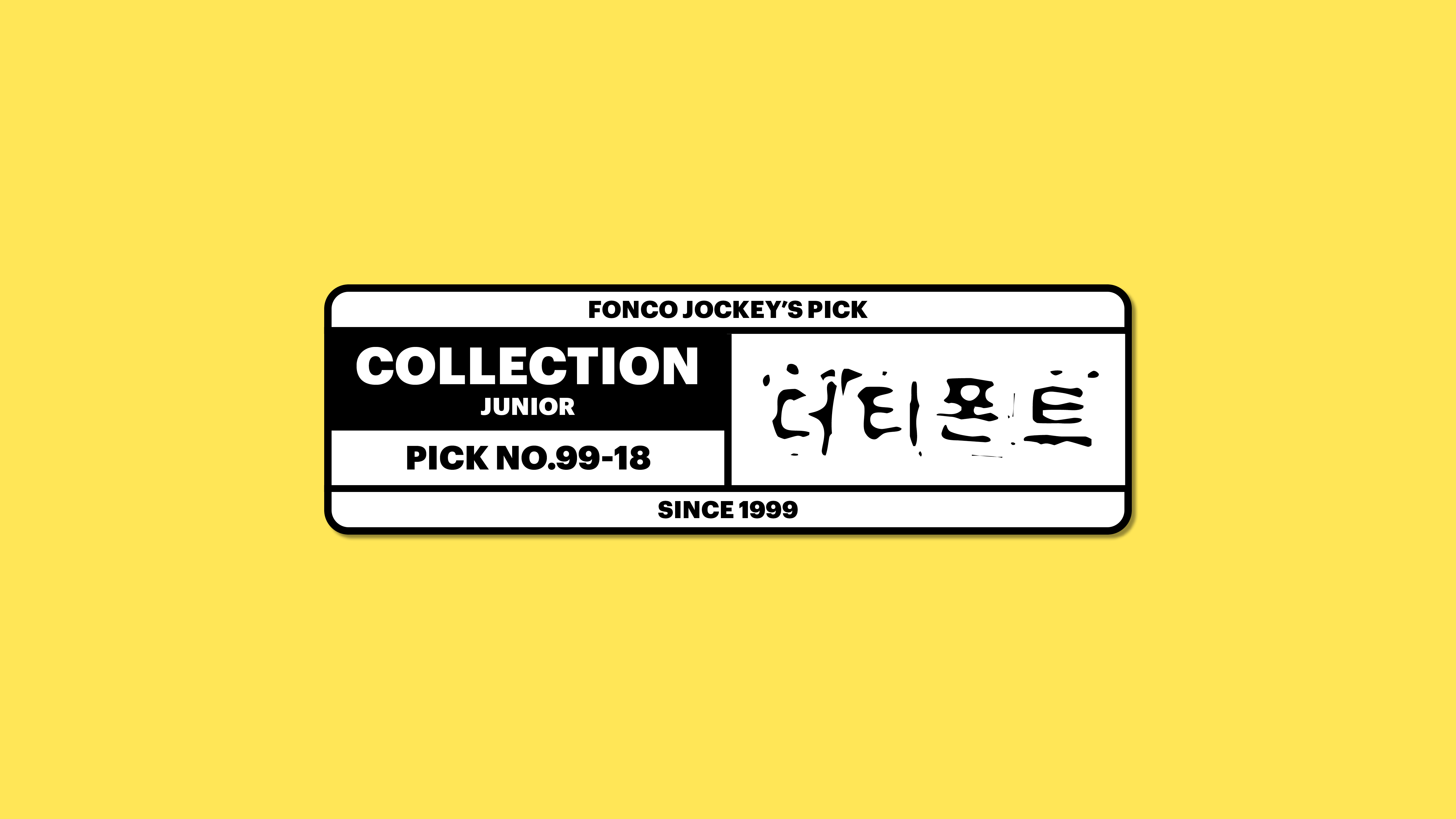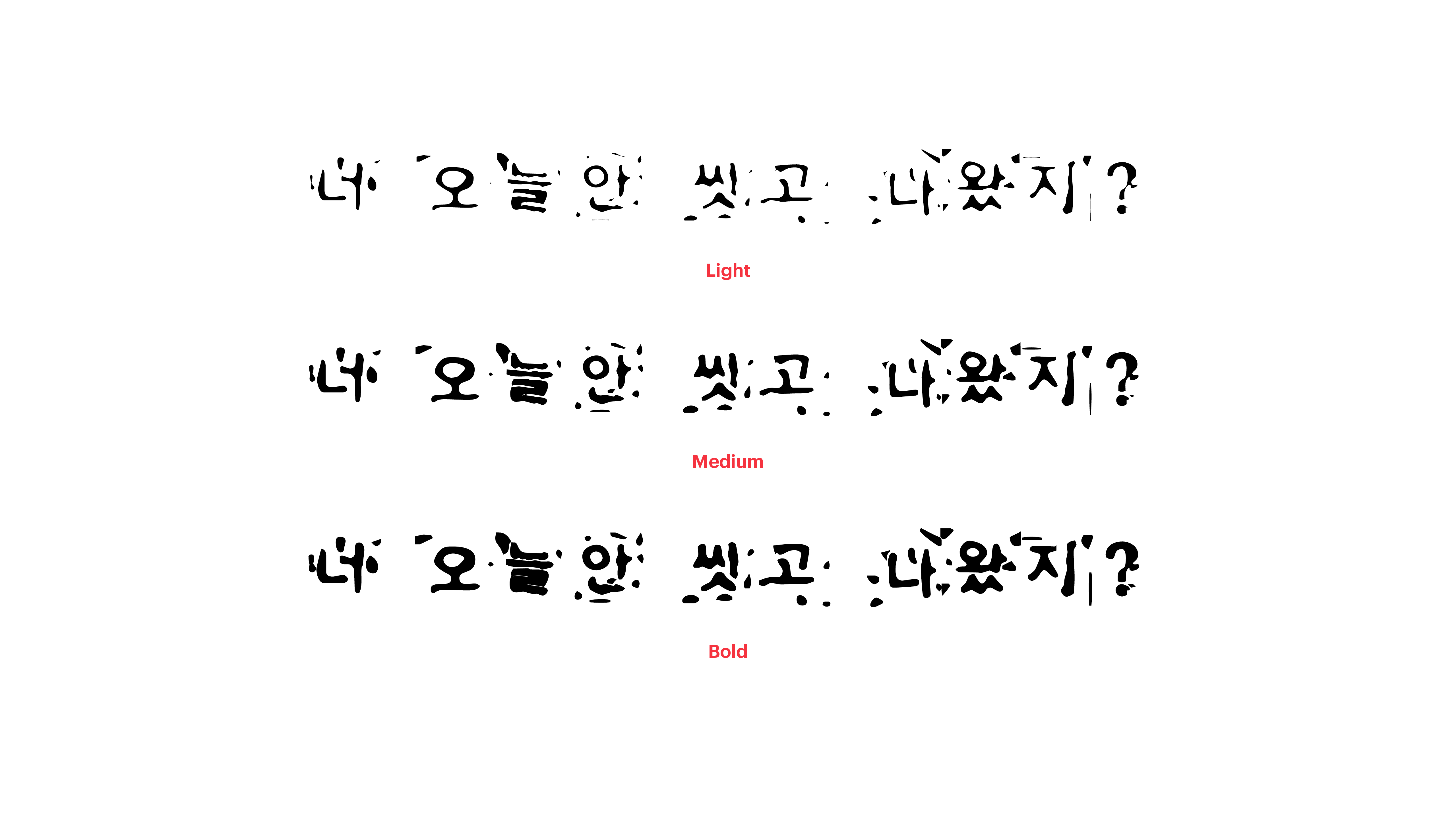
솔직하게 이야기해 보겠습니다. 폰코가 폰고수*이긴 하지만 폰트 만드는 건 꽤 까다로운 일이라고요! 그래서 아무런 제약 없이 자유롭게 디자인해보았습니다. 평소에 안고 있던 창작의 고뇌를 탈탈 쏟아냈기 때문에 노이즈로 가득한 감성적 폰트가 탄생했어요. 그러니 제 생각에 공감하는 여러 창작자 여러분, 오늘은 더티폰트로 창작의 고통에 대한 이야기를 적어보는 거 어때요?
Yoon 더티폰트